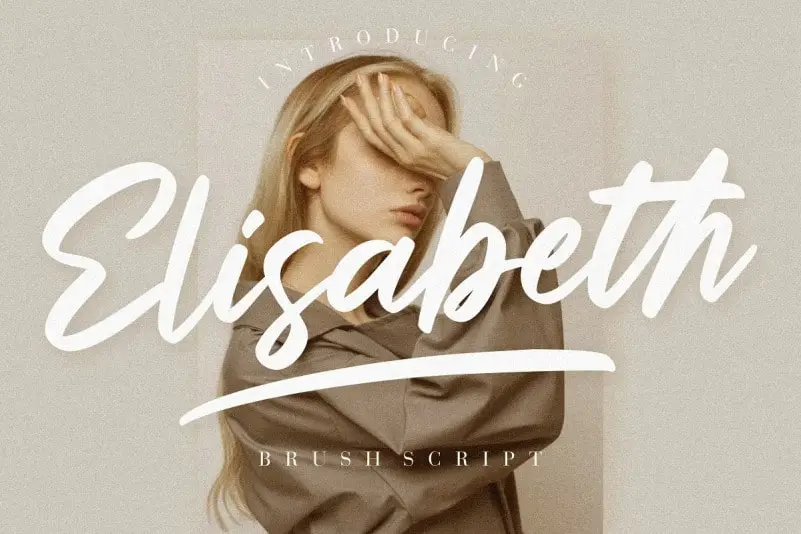
Elisabeth Script Font – Fonte Grátis
Elisabeth Script Font – Download Grátis
Elisabeth Script Font
Elisabeth Script Font é uma fonte de estilo brush de alta qualidade criada pelo Creatype Studio que transmite a sensação do texto realinhado à mão com texturas de escrita aparentemente brilhante e robusta. Esta escolha de letra não apenas proporcionará um toque sofisticado e luxuoso aos seus projetos, mas também oferecerá um elemento único e autêntico às suas publicações digitais ou impressas. Seja para criar cartões de visita elegantes, capas de livros com um visual artístico impressionante ou até mesmo adicionar um toque especial a mensagens de texto em uma newsletter, Elisabeth Script Font é ideal para quem procura um estilo elegante e autêntico na sua tipografia.